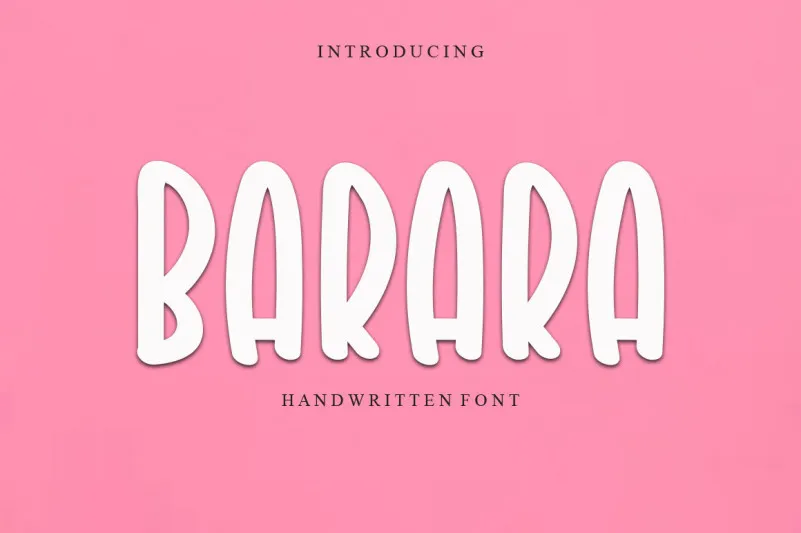
A Barara Font é uma opção única e divertida para projetos digitais do dia a dia. Seja para adicionar um toque criativo à sua publicação no Instagram ou para criar uma escrita delicada nas suas tarefas DIY, esta fonte irá transformar qualquer ideia em arte perfeita. Ela é ideal tanto para profissionais de design como para pessoas que buscam expressar seu estilo pessoal em projetos manuais. Com sua graça e simplicidade, a Barara Font é uma opção versátil e divertida para aqueles que querem adicionar um toque de personalização à suas criações digitais ou artesanais.